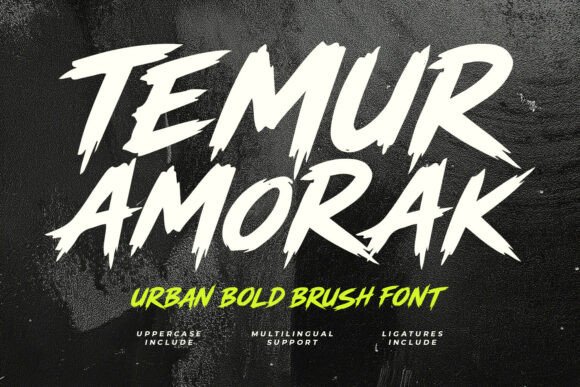
Temur Amorak Urban Bold Brush Font
Поиск подходящих элементов дизайна может быть сложным, но Temur Amorak Urban Bold Brush Font предлагает исключительную коллекцию, которая мгновенно улучшит вашу работу.
Созданный с высокой точностью, Temur Amorak Urban Bold Brush Font предоставляет чистые векторы, плавную типографику и коммерческую лицензию для вашего спокойствия.
Создаете ли вы продукты POD (печать по требованию), свадебные приглашения или графику для социальных сетей, Temur Amorak Urban Bold Brush Font станет идеальным выбором.